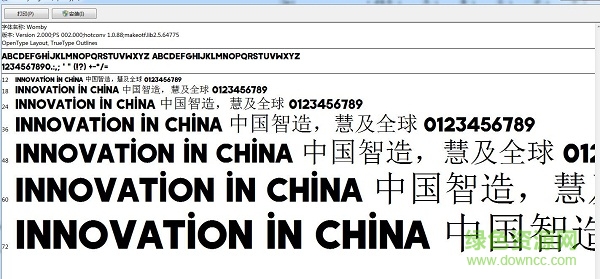
軟件介紹 軟件標簽: womby字體 無襯線字體 womby regular字體是一款粗黑的無襯線字體,字形端正,線條粗細一致,視覺元素豐富,既具有現(xiàn)代氣息而又不個性,適合用作海報標題或用在logo設(shè)計方面,喜歡的朋友快來下載吧!womby字體特征1.字體結(jié)構(gòu)合理,筆劃前后統(tǒng)一;2.筆形剛健有力,個性豪放,視覺沖擊力強;3.適用于布置櫥窗、裝潢商品、制作廣告、設(shè)計書刊等;英文粗體推薦futura bt heavy 授權(quán):免費軟件 WinAll, WinXP, Win7大?。?50KB語言:中文futurabtheavy字體是futura系列中較粗的一款無襯線字體,非常經(jīng)典,字形干凈,轉(zhuǎn)折非常鋒利,幾何性強,常常用于各類平面設(shè)計中,喜歡的朋友快來下載吧!英文字體特點【現(xiàn)代字體】極細的發(fā)絲襯線,筆畫粗細對比下載地址ruixiansunheiheavygb字體 授權(quán):免費軟件 WinAll, WinXP, Win7大?。?.4M語言:中文ruixiansunheiheavygb1.0字體是一款由銳字工房打造的黑體字體,字心開闊,線條粗黑,設(shè)計感十足,應(yīng)用性強,適合用于標題設(shè)計,歡迎大家免費下載!ruixiansunheiheavygb字體特點1.字體粗細度采用了相對較粗的設(shè)計;下載地址womby 字體安裝方法直接將字體文件復(fù)制到C:\Windows\Fonts文件夾即可完成安裝(Win7用戶可直接右鍵選擇“安裝”菜單進行安裝)。 軟件截圖 上一張下一張(1 / 1) 安裝詳細截圖 其他版本下載 標題 大小 更新日期 下載 下載地址 電腦版 womby字體 點擊報錯 軟件無法下載或下載后無法使用,請點擊報錯,謝謝! 關(guān)閉報錯反饋 請描述您所遇到的錯誤,我們將盡快予以修正,謝謝! *必填項,請輸入內(nèi)容 本類最新 sounso beauty字體 spyced哥特英文字體 ttf版 zerodegrees字體 the next font ttf版 coolvetica font keep calm ttf 免費版 相關(guān)文章 Word利用超級鏈接快速調(diào)出指定文檔 Windows XP下無法安裝字體的解決方案 Windows 7下虛擬機安裝Chrome OS實戰(zhàn) 淺談DVD-ROM光驅(qū)工作原理 CD-ROM CD-R CD-RW之間的區(qū)分 安裝Windows7設(shè)置拒絕自動產(chǎn)生100MB分區(qū)方法 用戶評論 熱門評論 最新評論 發(fā)表評論 查看所有評論(0) 昵稱: 請不要評論無意義或臟話,我們所有評論會有人工審核. 字數(shù): 0/500 (您的評論需要經(jīng)過審核才能顯示)